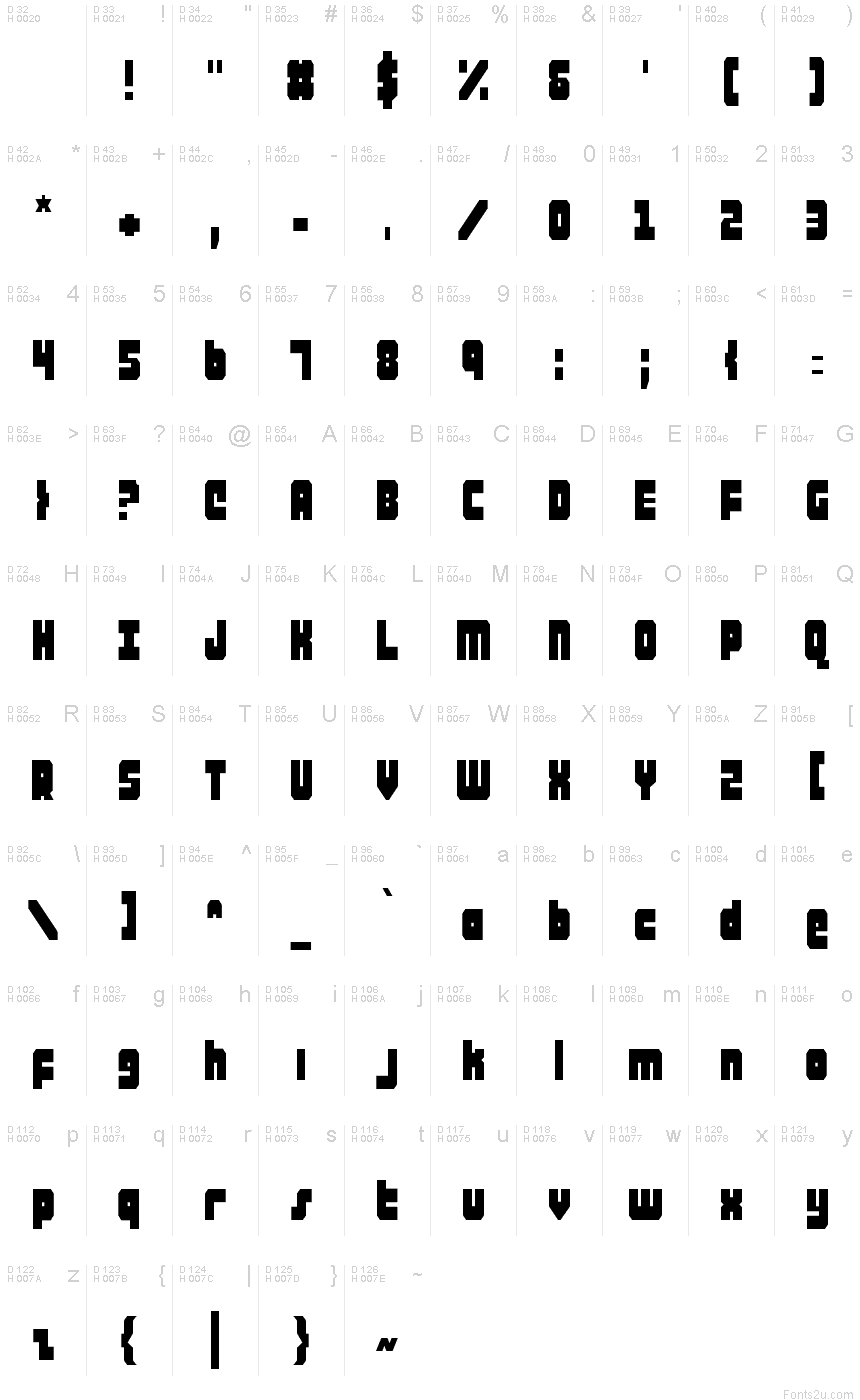
Alpha Taurus Condensed od Iconian Fonts to darmowy krój pisma typu display w klimacie techno, o wyrazistym, „arkadowym” charakterze. Litery są wysokie i ciasno ułożone, a ostre cięcia oraz masywne pionowe linie nadają całości robotyczny, industrialny wygląd, przywodzący na myśl sprzęt do gier retro.
Świetnie sprawdza się na plakatach sci-fi, w logo gier, planszach tytułowych, brandingu sportowym czy grafikach na YouTube, wszędzie tam, gdzie krótkie słowa wymagają zwartej i silnej formy. Jako darmowy font, sprawdzi się również w menu, oprawach streamów czy na okładkach albumów, szczególnie jeśli szukasz tego kwadratowego, mechanicznego rytmu, unikając przy tym wyświechtanych futurystycznych klisz.